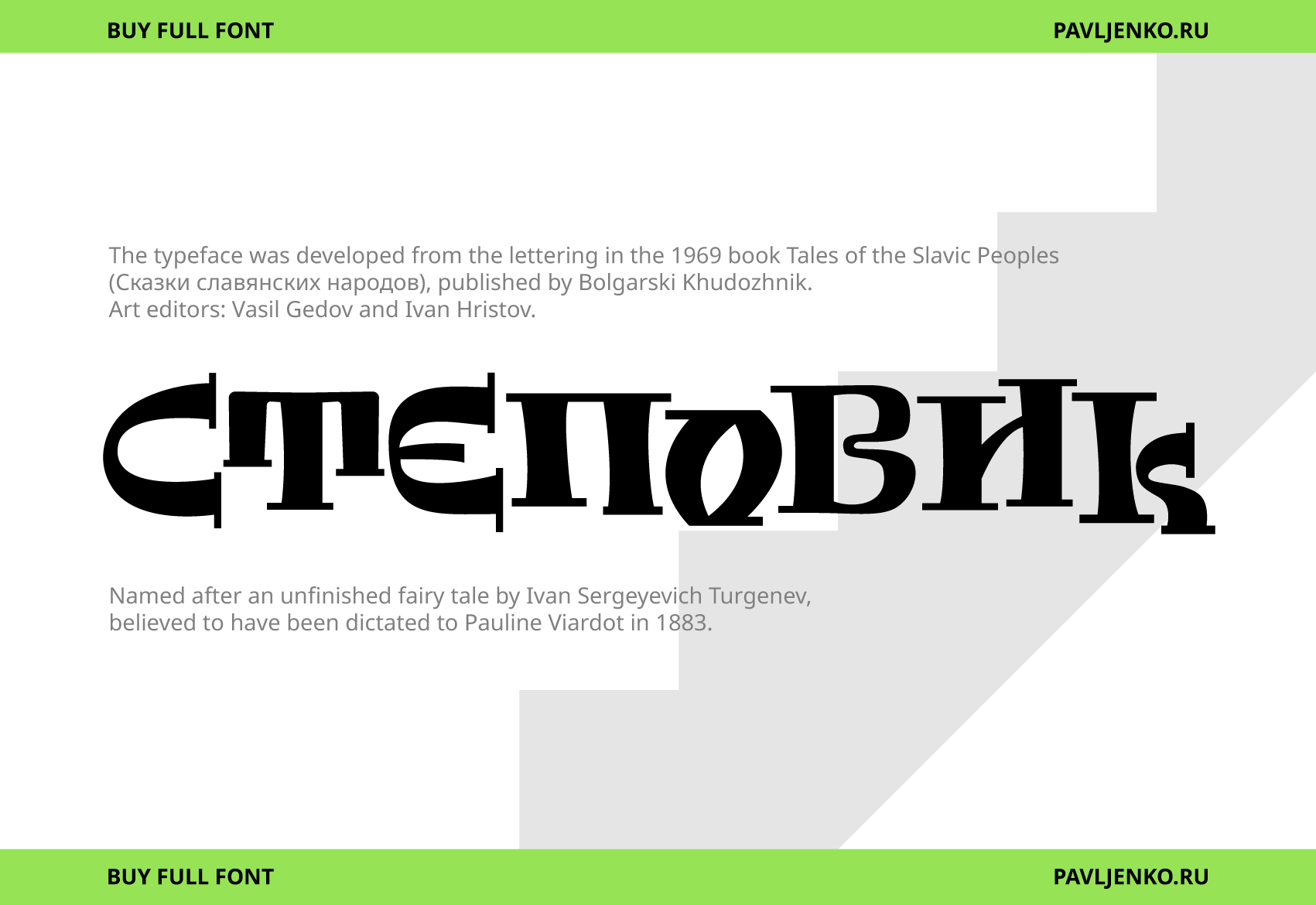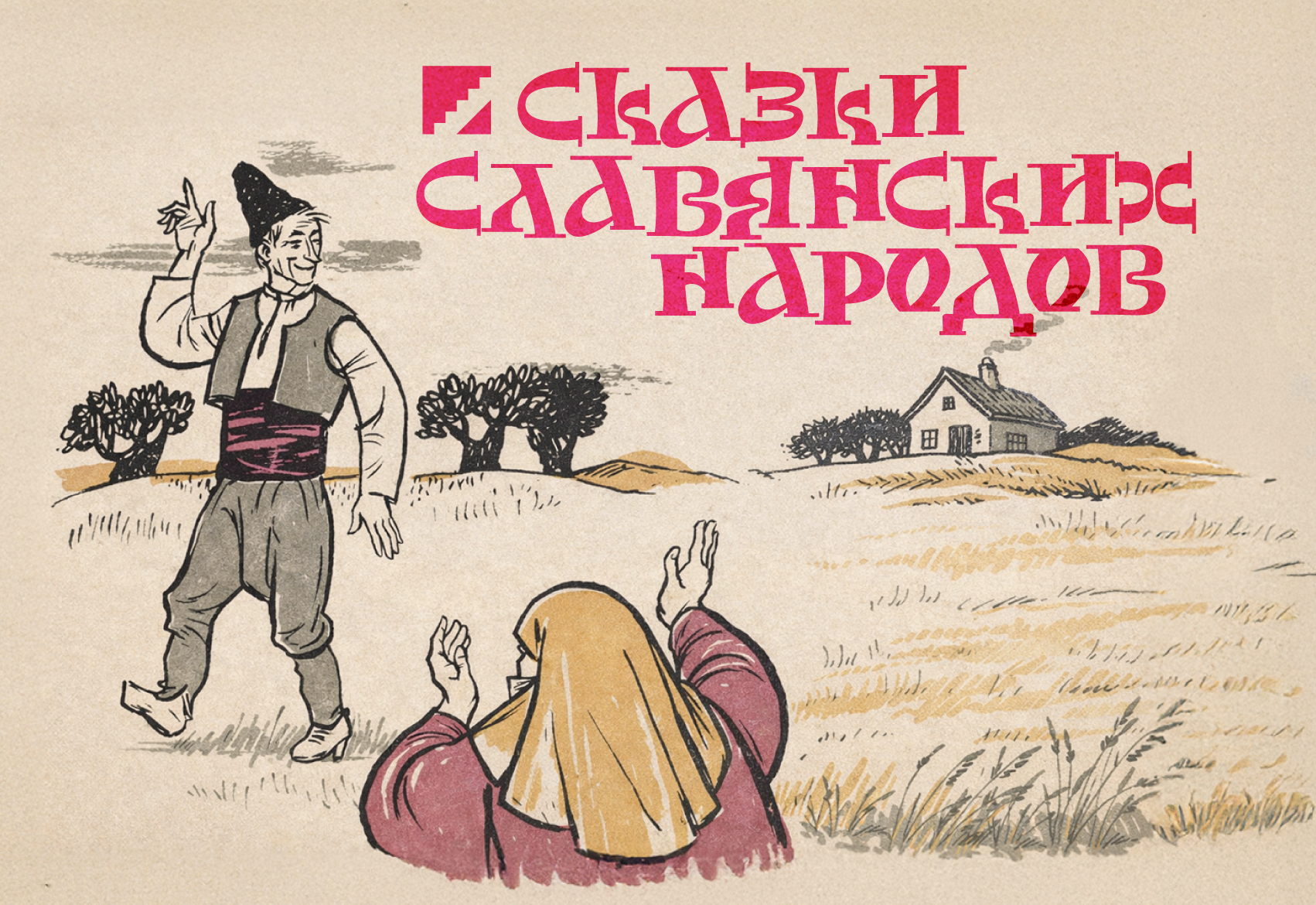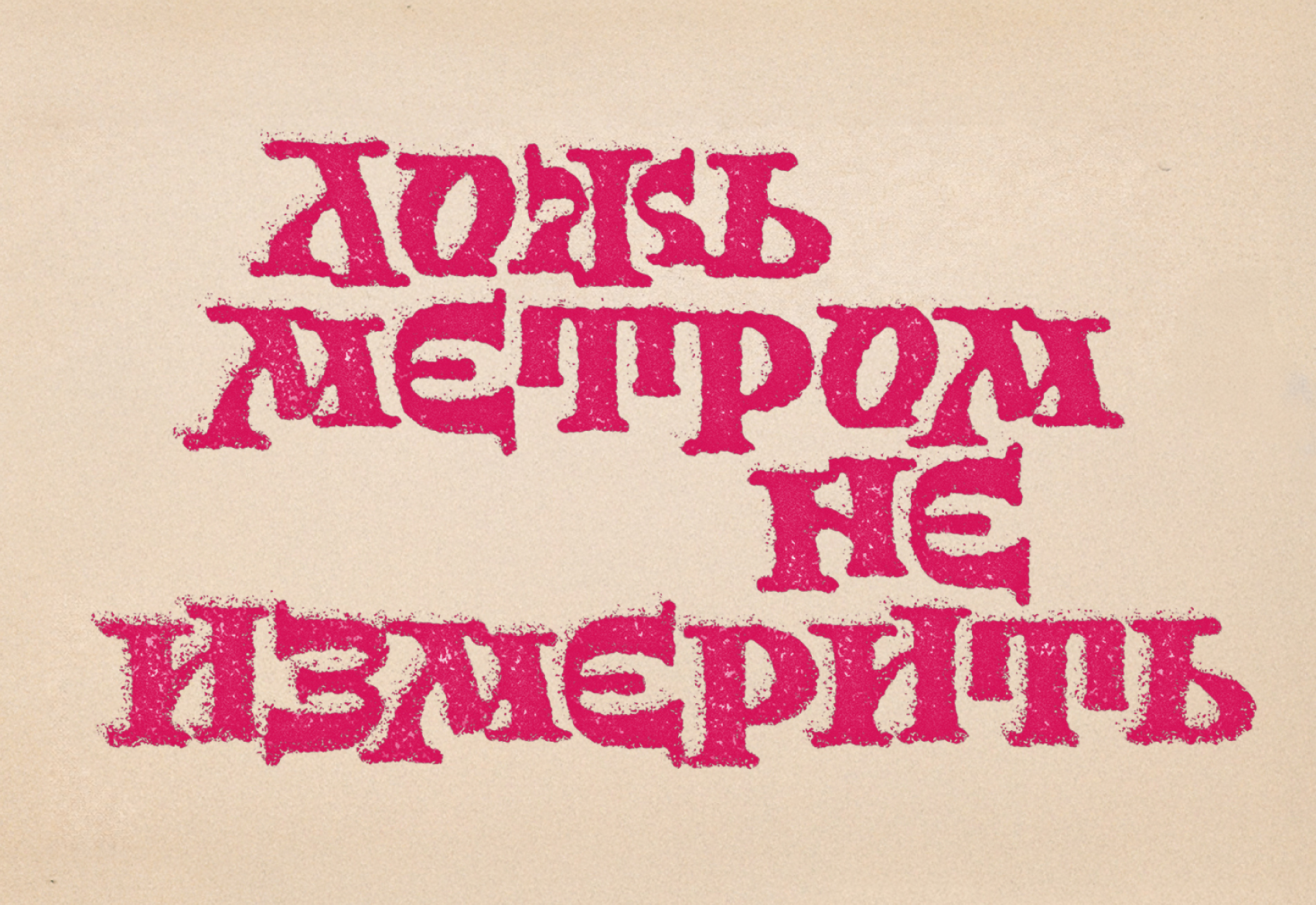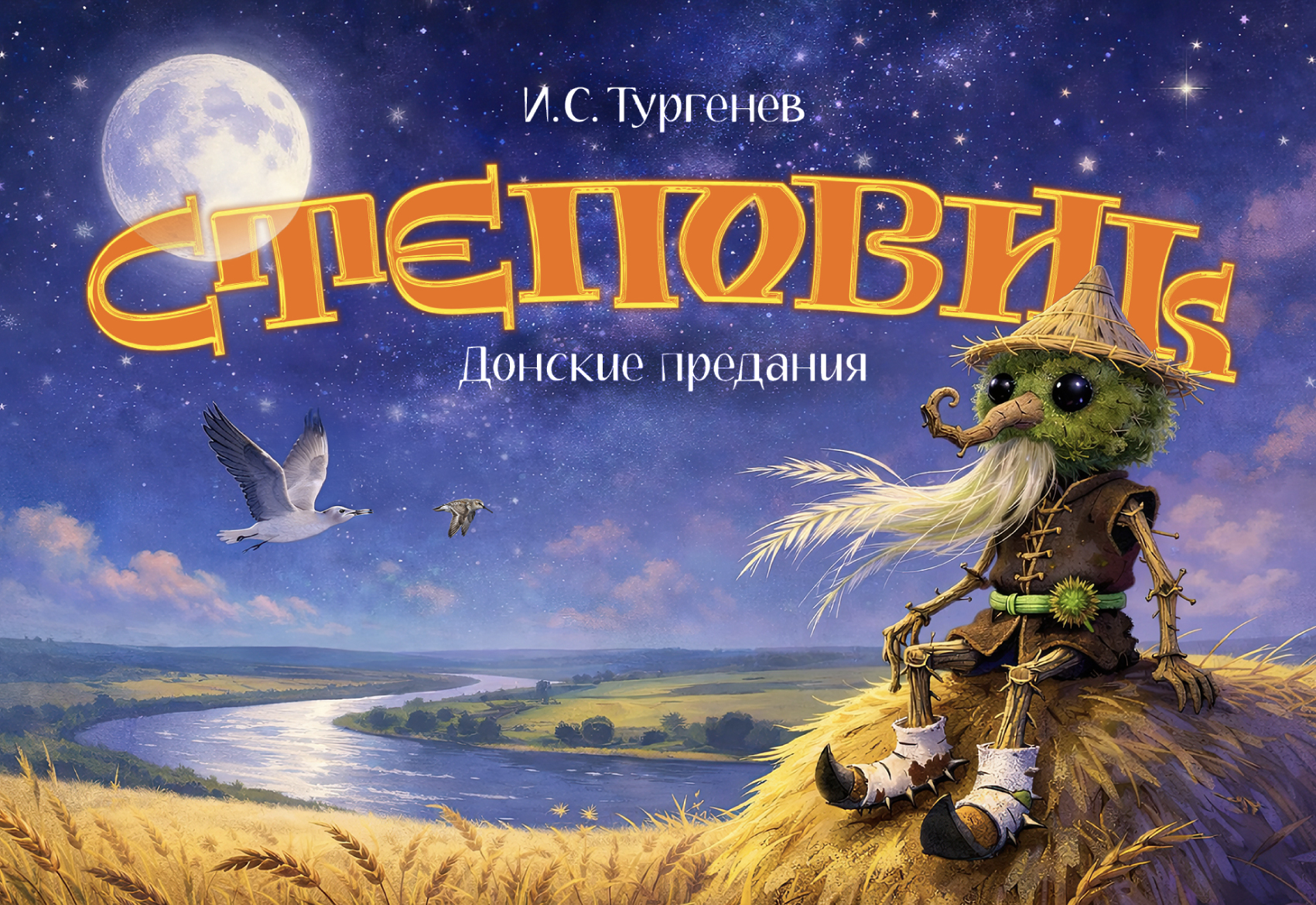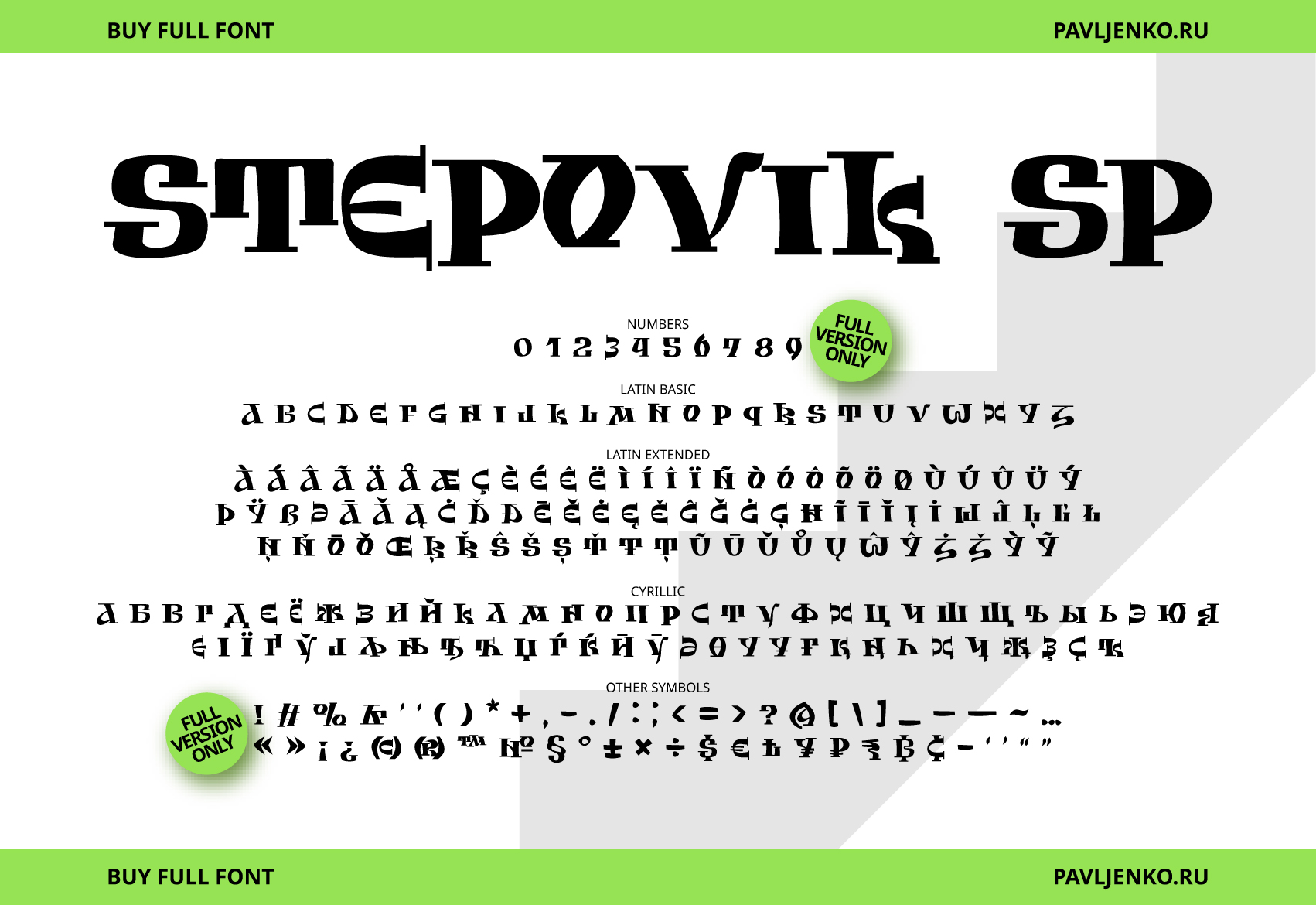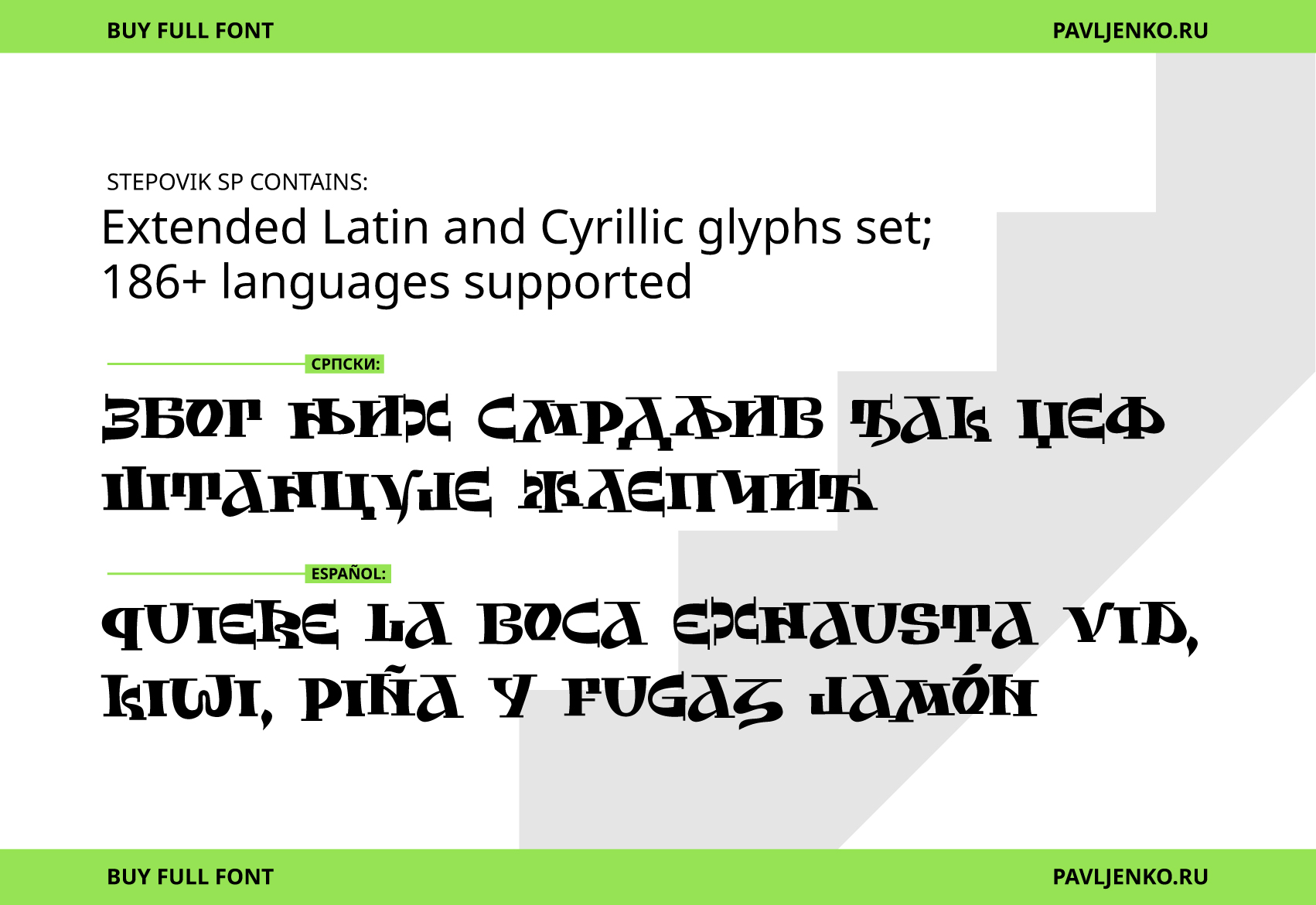
Stepovik SP — акцидентный шрифт в народном стиле с живым, слегка «пляшущим» ритмом. Его рисунок наследует и переосмысливает славянскую уставную традицию: крупные силуэты, врезы и нестандартные соединения создают рукотворное впечатление, похожее на резьбу по дереву или ручной штамп. Лучше всего шрифт раскрывается в крупных кеглях — в заголовках, на обложках, постерах, упаковке и в логотипах, когда нужен фольклорный характер и узнаваемая славянская эстетика. В комплекте — расширенная версия шрифта и электронная лицензия. Подойдет дизайнерам брендинга, упаковки и заголовочной графики с народным акцентом.
| Designer | Sasha Pavljenko |